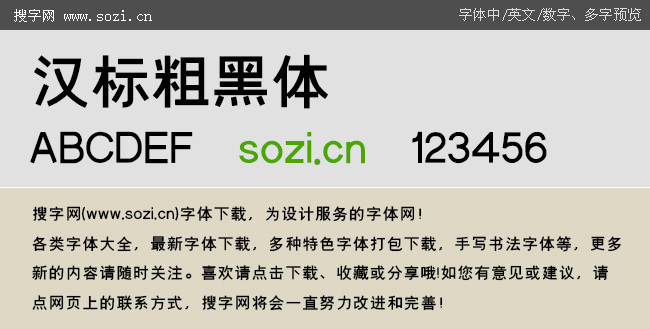
漢標(biāo)粗黑體
搜字網(wǎng)給大家提供一款漢標(biāo)粗黑體中文字體下載,漢標(biāo)粗黑體字體筆畫清朗有勁,簡約美觀。適用于大標(biāo)題、包裝設(shè)計、海報設(shè)計等應(yīng)用。(本字體為個人非商用版,如需要商用請聯(lián)系官方購買版權(quán))